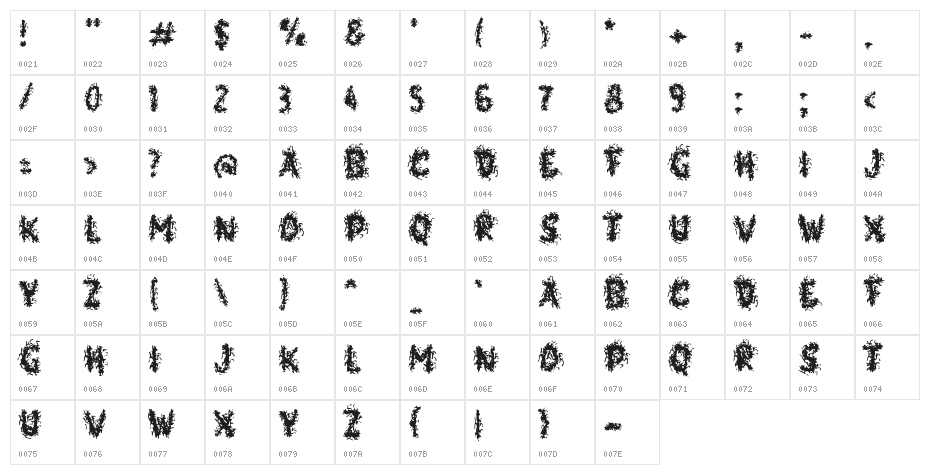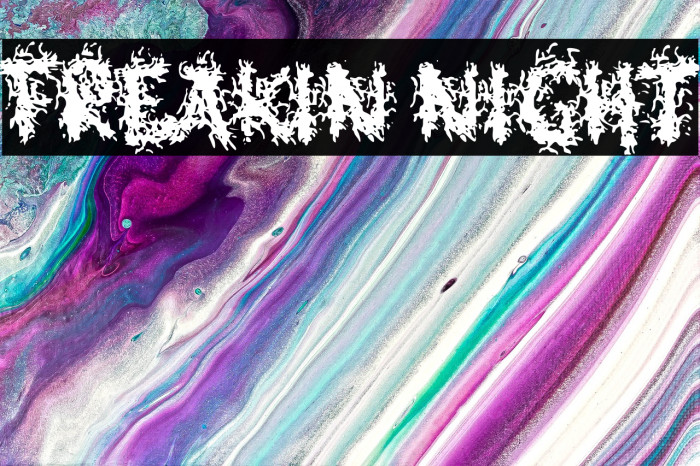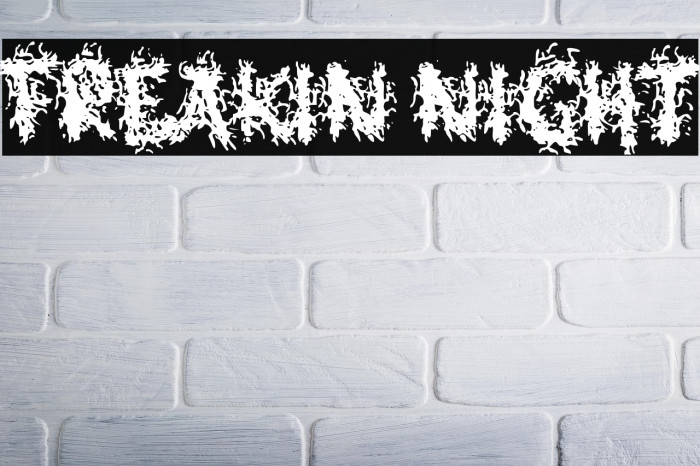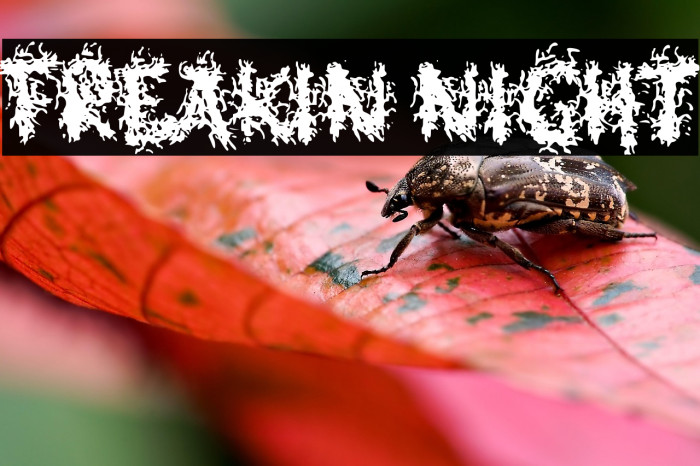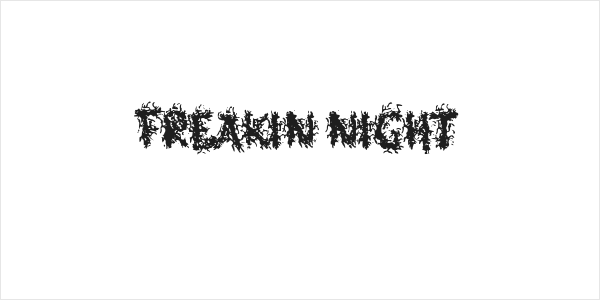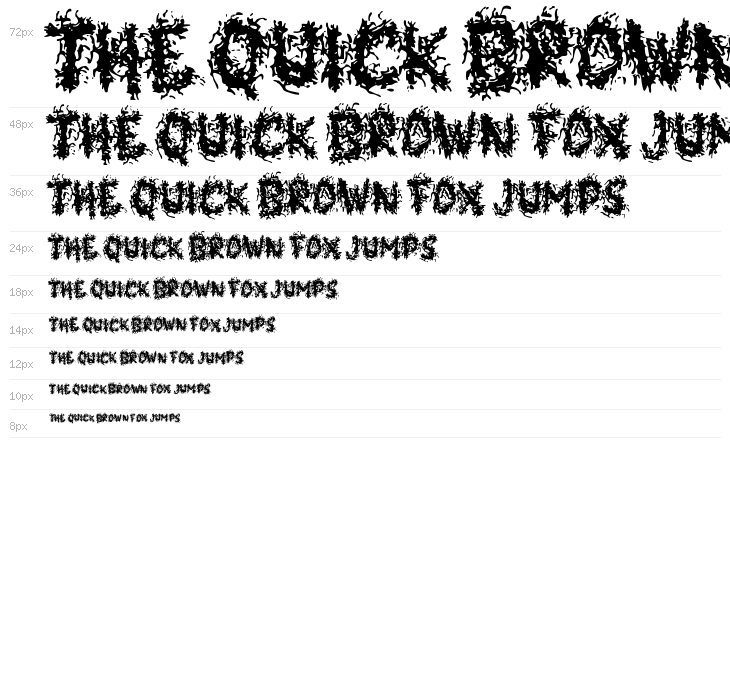
Freakin Night Font
| مشاريع مقترحة | Perfect for Halloween posters, horror movie titles, haunted house flyers, and any project needing a spooky or edgy vibe. |